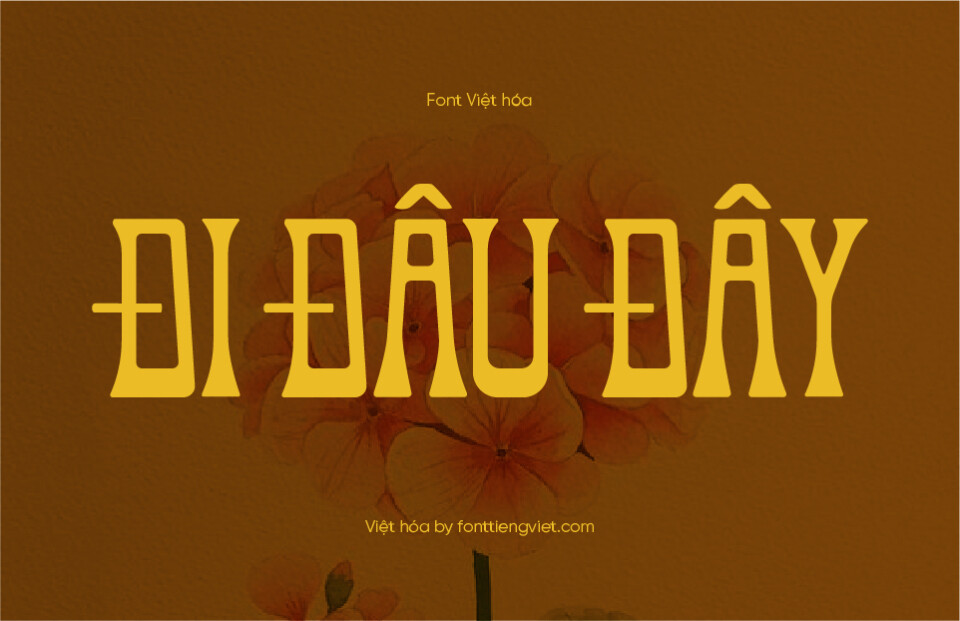
Font Việt hóa 1FTV Sagitarion
Giới thiệu về bộ Font Việt hóa 1FTV Sagitarion độc đáo
Trong thế giới sáng tạo, việc lựa chọn một Font Miễn Phí chất lượng luôn là ưu tiên hàng đầu của các nhà thiết kế. Font Việt hóa 1FTV Sagitarion nổi bật như một giải pháp hoàn hảo, mang đến vẻ đẹp hiện đại, tinh tế và đầy tính nghệ thuật. Được chuyển ngữ tỉ mỉ để phù hợp với bảng mã tiếng Việt, bộ phông chữ này giúp người dùng dễ dàng thể hiện ý tưởng mà không lo lỗi hiển thị dấu câu hay các ký tự đặc biệt.
Đặc điểm nổi bật của Font Việt hóa 1FTV Sagitarion
Thiết kế sang trọng và chuyên nghiệp
Bộ Font Việt hóa 1FTV Sagitarion sở hữu những đường nét thanh mảnh nhưng vô cùng chắc chắn. Cấu trúc chữ được tối ưu hóa để đảm bảo độ tương phản cao, tạo cảm giác chuyên nghiệp cho mọi ấn phẩm truyền thông. Đây là lựa chọn lý tưởng cho các bạn học sinh trong việc làm báo tường, trang trí slide thuyết trình hoặc cho các thầy cô giáo khi thiết kế giáo án điện tử sinh động.
Tính ứng dụng linh hoạt trong nhiều dự án
Không chỉ giới hạn trong trình bày văn bản, Font Việt hóa 1FTV Sagitarion còn phát huy tối đa sức mạnh khi ứng dụng vào thiết kế logo, bìa sách, và banner quảng cáo. Sự linh hoạt trong kiểu dáng giúp phông chữ này dễ dàng kết hợp với nhiều phong cách khác nhau, từ cổ điển đến hiện đại, giúp sản phẩm của bạn luôn bắt mắt và thu hút người xem ngay từ cái nhìn đầu tiên.